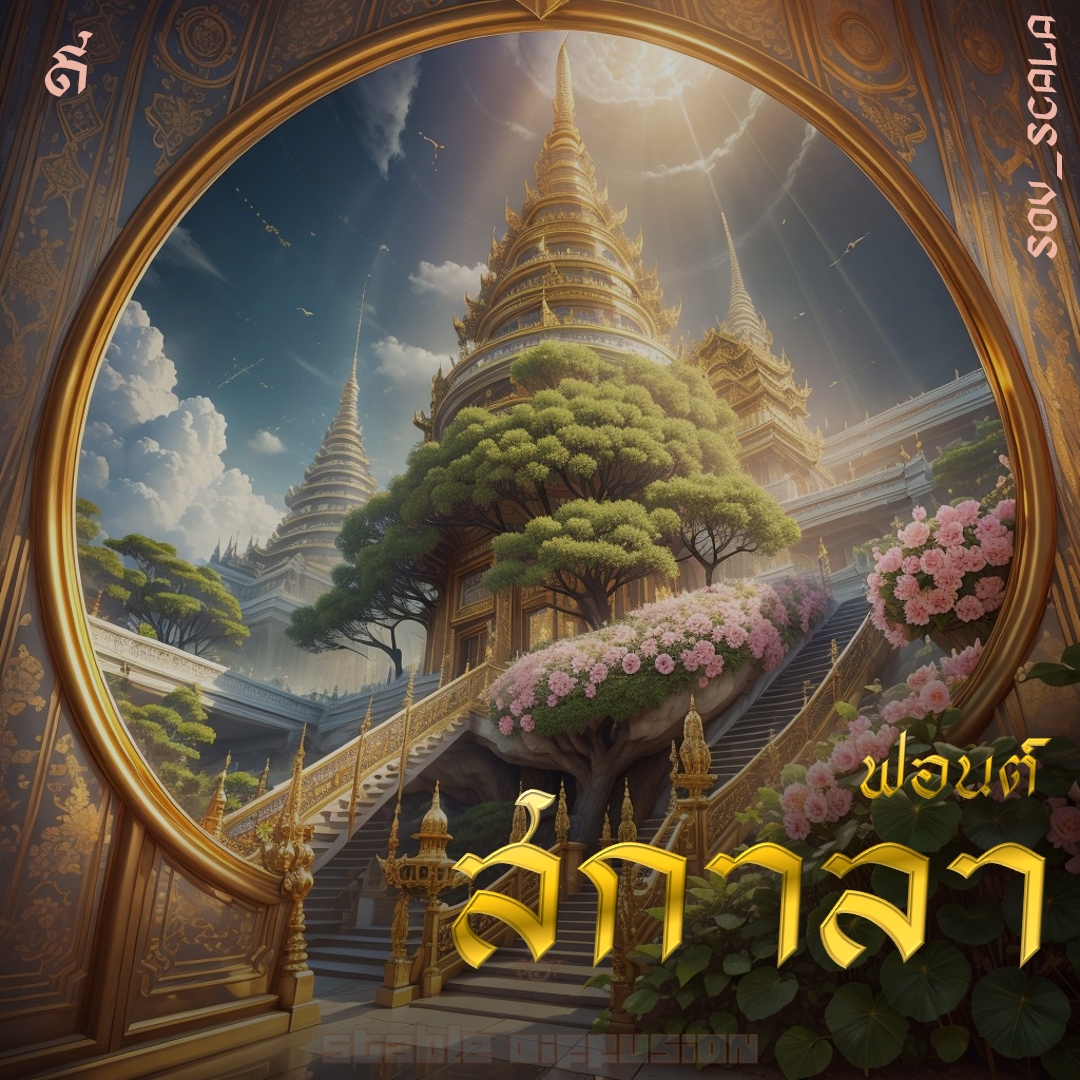
ฟอนต์ สกาลา
ฟอนต์สกาลา ต้นทางจากป้ายโรงภาพยนต์สกาลา แกะอัตลักษณ์จากอักษร 4 ตัว ที่เหลือด้นเอา
ชื่อฟอนต์ : สกาลา
ฟอนต์สกาลา ต้นทางจากป้ายโรงภาพยนต์สกาลา แกะอัตลักษณ์จากอักษร 4 ตัว ที่เหลือด้นเอา